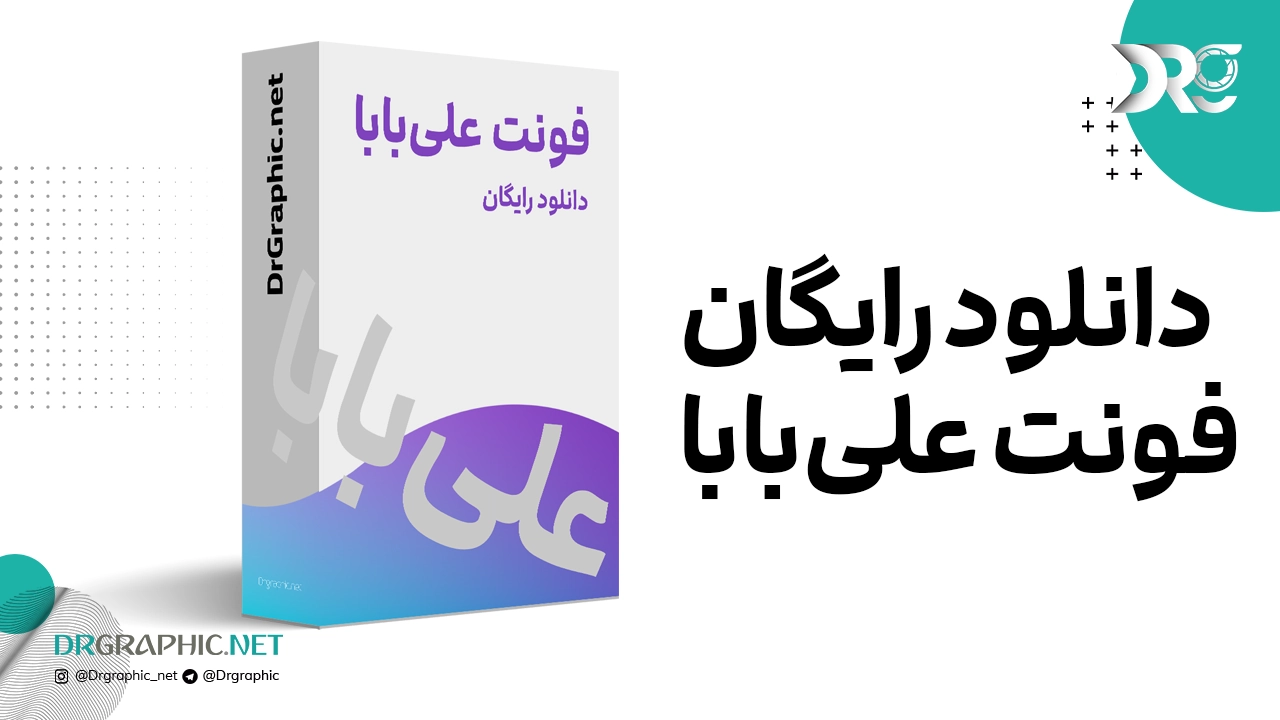
فونت فارسی علی بابا
این فونت زیبا در وبسایت رسمی فروشگاه بلیط علی بابا استفاده شده است.
وزن‌ها
فونت اختصاصی علی‌بابا چهار وزن دارد؛ دو وزن معمولی و نازک که از آن‌ها برای متن بدنه و دو وزن سنگین و سیاه که از آن‌ها برای عناوین استفاده می‌کنیم. این وزن‌ها هرکدام به‌دقت برای استفاده در موقعیت‌ها و کارکردهای مشخصی دیزاین شده‌اند. بنابراین لازم است هنگام استفاده از آن‌ها به ملاحظات ارتباطی توجه کنیم. به طور مشخص، باید بدانیم چه پیامی از طریق چه رسانه‌ای به چه مخاطبی منتقل خواهد شد و مهم‌تر از آن، سلسله‌مراتب پیام و محتوا به چه ترتیبی طراحی شده است.
ویژگی‌های فونت علی‌بابا
در دیزاین علاوه‌بر ویژگی‌های اصلی، مجموعه‌ای از ویژگی‌های تکمیلی پیش‌بینی کرده‌ایم که باعث غنای تایپوگرافی می‌شود .
این ویژگی ها عبارت اند از :
لیگیچرها (Ligature)، فرم‌های جایگزین، کشیده‌ها، مجموعه‌های سبکی، و اعداد متنی و جدولی
فونت علی بابا یکی از محبوب‌ترین فونت‌ها در دنیای طراحی و گرافیک است که بسیاری از طراحان و کاربران از آن استفاده می‌کنند. این فونت با استایل منحصر به فرد و زیبا خود، می‌تواند به طرح‌های شما جذابیت و زیبایی بیشتری ببخشد. اگر به دنبال یک فونت با شخصیت و جذاب هستید، حتما بیایید فونت علی بابا را دانلود کنید و از آن در طراحی‌های خود استفاده کنید.